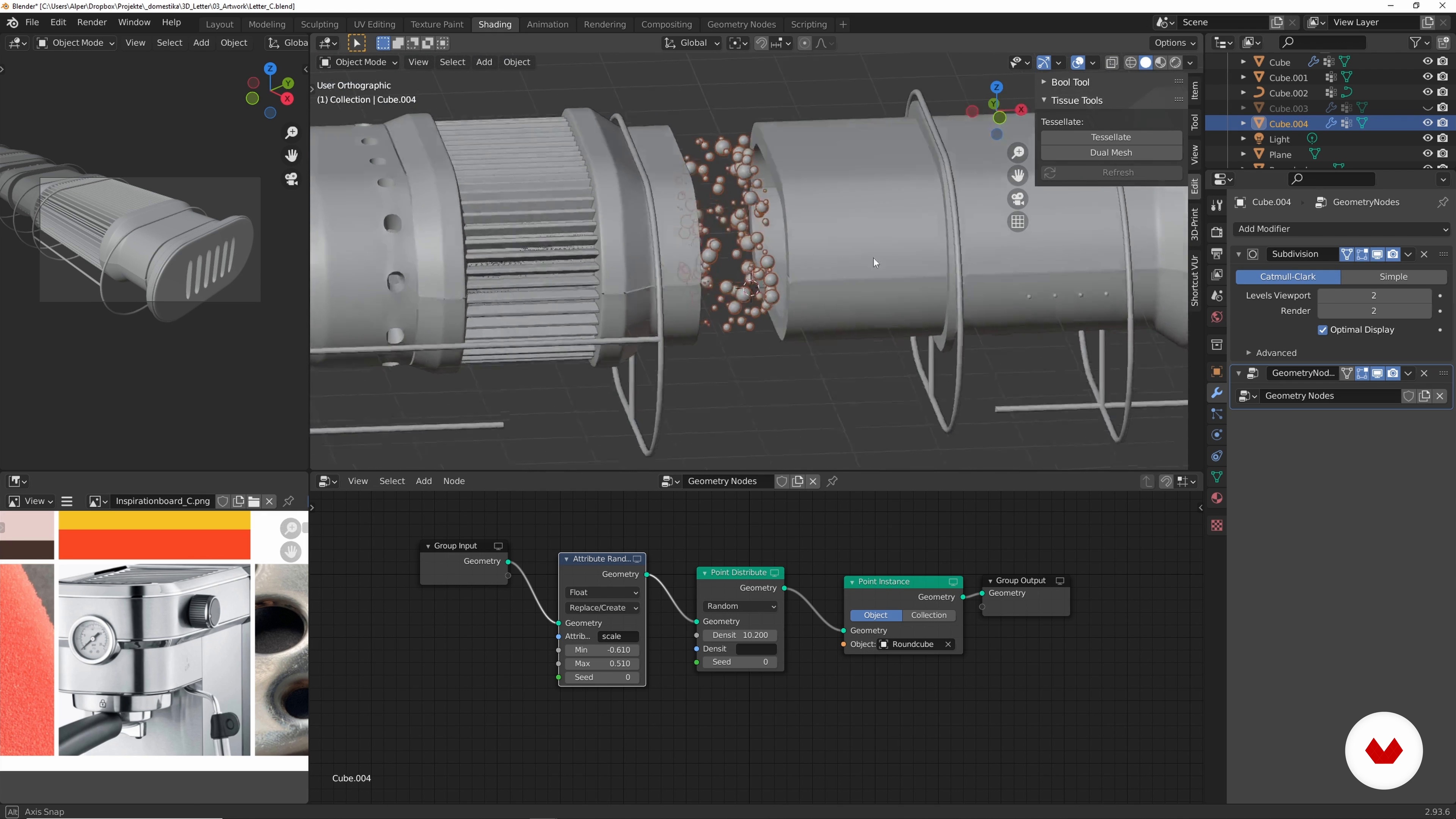
3D-Typografie mit Blender: Designe einzigartige Buchstaben
Modellierung der Elemente und Module 3
Über die Videolektion: Modellierung der Elemente und Module 3
“Ich empfehle dir, nichts exakt nachzubilden, sondern mit Elementen und Formen zu arbeiten, die du kennst. Die fertig erstellten Module können später, wenn die Buchstabenform angewendet wird, noch geändert und angepasst werden. ”
In dieser Videolektion behandelt Alper Dostal das Thema: Modellierung der Elemente und Module 3, das Teil dieses Domestika-Onlinekurses ist: 3D-Typografie mit Blender: Designe einzigartige Buchstaben. Lerne, 3D-Buchstaben mit verschiedenen Techniken in Blender zu modellieren und spiele mit surrealen Kontrasten zwischen Farben, Materialien und Texturen.
“ Modellierung der Elemente und Module Es könnte ein bisschen größer sein, also vergrößern wir es einzeln noch. Alle ein bisschen größer machen. Es wäre noch interessant, dass wir entlang der Module diese Form anbringen, damit die Buchstabenform betont wird. Dann können wir dieses Element rauskopieren mit Shift + D, drehen es um 90° und platzieren es ungefähr in dem Bereich. Einmal unten. Das gleiche vielleicht auch weiter oben bzw. das Element wiederholt sich. Oder an der Rückseite entlang, so, dass es mittig verläuft. Man kann nach Gefühl gehen, wie es einem interessant erscheint. Ich ach...”
Zusammenfassung des Kurses: 3D-Typografie mit Blender: Designe einzigartige Buchstaben